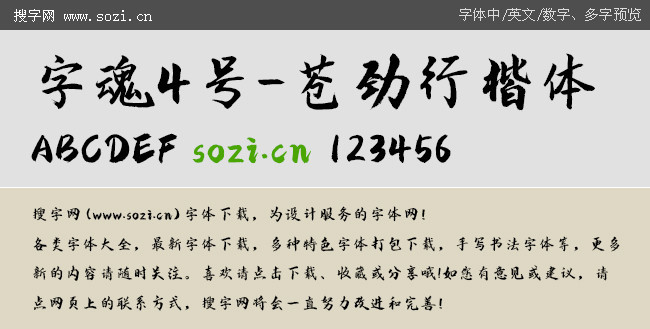
字魂4號(hào)-蒼勁行楷體
搜字網(wǎng)提供一款字魂4號(hào)-蒼勁行楷體中文字體下載,該字體是一款毛筆書法手寫字體,該字體包含6763個(gè)中文、字母、 符號(hào)和數(shù)字,具有有力、穩(wěn)重、豪放、手寫風(fēng) 的風(fēng)格,可以滿足您設(shè)計(jì)上的各種需求,該字體主要用于企業(yè)慶典、社交、屏幕、印刷品、屏顯、印章、企業(yè)店鋪、電商、H5 等場(chǎng)景。